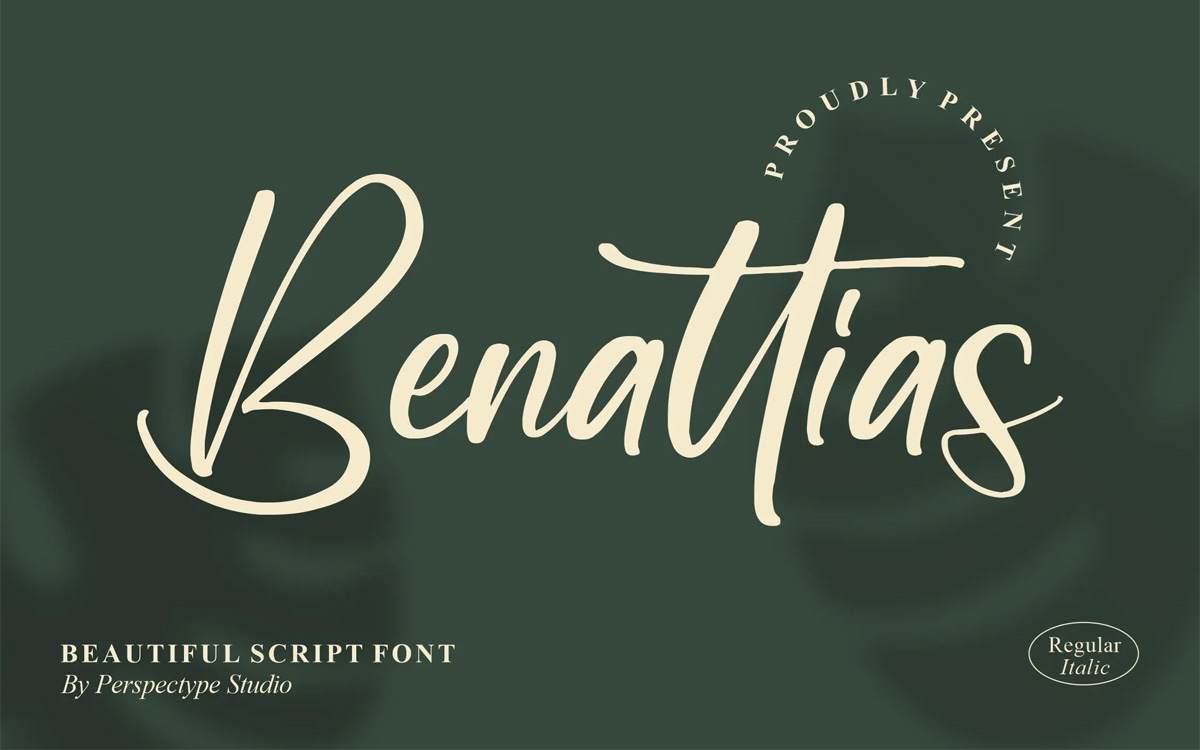
Font chữ viết tay, chữ ký mềm mại cho thiệp cưới, đám cưới TH Benattias
Trong thiết kế thiệp cưới, việc lựa chọn bộ font chữ phù hợp đóng vai trò quyết định tạo nên ấn tượng đầu tiên sang trọng và tinh tế cho ngày trọng đại. TH Benattias là bộ font chữ viết tay, chữ ký mềm mại đỉnh cao được thiết kế dành riêng cho các ấn phẩm đám cưới, mang đến phong cách nghệ thuật quyến rũ và xúc cảm chân thành. Với đường nét uốn lượn tự nhiên, TH Benattias chắc chắn sẽ nâng tầm đẳng cấp cho tấm thiệp cưới của bạn, biến từng nét chữ thành một tác phẩm nghệ thuật đong đầy hạnh phúc.
Dù bạn là một designer chuyên nghiệp đang tìm kiếm bộ chữ hoàn hảo cho bộ sưu tập mẫu thiệp mới, hay là cô dâu chú rể muốn tự tay chăm chút cho ngày vui của mình, TH Benattias đều sẵn sàng đáp ứng những tiêu chuẩn khắt khe nhất về tính thẩm mỹ. Hãy cùng khám phá chi tiết về bộ font chữ viết tay cực kỳ độc đáo này ngay dưới đây.
Vẻ Đẹp Độc Bản Từ TH Benattias – Font Chữ Viết Tay, Chữ Ký Mềm Mại Cho Thiệp Cưới Và Đám Cưới Sang Trọng
Ngày cưới là sự kiện trọng đại nhất trong cuộc đời mỗi người, nơi từng chi tiết nhỏ nhất từ không gian, hoa trang trí cho đến tấm thiệp mời đều cần chứa đựng sự tỉ mỉ và tâm huyết. Việc ứng dụng font chữ viết tay, chữ ký mềm mại cho thiệp cưới, đám cưới TH Benattias chính là bí quyết giúp bạn gửi gắm lời mời trân trọng nhất tới những người thân yêu. Không đơn thuần là các ký tự vô giác, TH Benattias thổi hồn vào không gian tiệc cưới bằng vẻ đẹp lãng mạn, phóng khoáng nhưng không kém phần quý phái.
Sở dĩ bộ font này tạo nên cơn sốt trong cộng đồng thiết kế đám cưới là nhờ sự kết hợp tài tình giữa nét bút lông mềm mại (brush script) và nghệ thuật viết chữ ký (signature calligraphy). Các đường nét của font TH Benattias có độ dày mỏng chuyển biến linh hoạt, mô phỏng chính xác nhịp điệu của bàn tay nghệ nhân khi nắn nót từng nét chữ. Sự tự nhiên này xóa tan cảm giác cứng nhắc của các font chữ máy tính thông thường, mang lại cảm giác thân thiện, ấm áp và vô cùng cao cấp.</p>
1. Thiết Kế Nét Chữ Mềm Mại, Bay Bổng Mang Tính Nghệ Thuật Cao
Tính năng nổi bật nhất của TH Benattias chính là cấu trúc nét chữ vô cùng uyển chuyển. Mỗi đường móc, nét uốn đều được tính toán tỉ mỉ để tạo nên sự cân bằng hoàn hảo giữa tính dễ đọc và vẻ đẹp nghệ thuật. Nét bút mang lại cảm giác phóng khoáng, nhẹ nhàng như những dải lụa mềm mại đang tung bay trong gió thu tiệc cưới.
Đối với các thiết kế thiệp cưới hiện đại, nét chữ viết tay này giúp tôn vinh tên của chú rể và cô dâu (Monogram/Couple Name), biến điểm nhấn chính trên tấm thiệp trở nên nổi bật và thu hút ánh nhìn ngay từ giây đầu tiên. Bên cạnh đó, font chữ còn giữ được độ thanh thoát dù ở kích thước lớn hay nhỏ, giúp trang trí các tiêu đề thiệp vô cùng ấn tượng.
2. Hệ Thống Ký Tự Thay Thế (Swashes) Phong Phú Cho Chữ Ký Độc Đáo
Một bộ font chữ ký đẳng cấp không thể thiếu các ký tự thay thế (Glyphs & Swashes) và TH Benattias đã làm xuất sắc điều này. Bộ font cung cấp hàng loạt tùy chọn nét gạch chân, nét bay ở đầu và cuối từ (Beginning & Ending Swashes), giúp người thiết kế biến tấu linh hoạt mà không sợ bị trùng lặp.
• Nét uốn đầu và cuối từ: Tạo cảm giác chữ viết tay tự nhiên như một chữ ký nghệ thuật chuyên nghiệp.
• Ligatures (Nét nối đôi): Các cặp chữ cái đặc biệt được nối liền mạch một cách tinh tế, xóa bỏ khoảng cách thô cứng giữa các ký tự.
• Bộ ký tự mở rộng: Cung cấp nhiều dạng nét uốn cho các chữ cái hoa, giúp các mẫu logo tên đám cưới trở nên độc bản.
3. Hỗ Trợ Tiếng Việt Trọn Vẹn, Chuẩn Tỷ Lệ Ký Tự
Rất nhiều bộ font script nước ngoài gặp phải rào cản lớn khi áp dụng vào tiếng Việt: các dấu thanh (sắc, huyền, hỏi, ngã, nặng) thường bị đè lên nét chữ hoặc làm mất đi vẻ thẩm mỹ vốn có. Tuy nhiên, TH Benattias đã được Việt hóa chỉn chu, đảm bảo giữ nguyên tinh thần thiết kế ban đầu.
Các dấu tiếng Việt trong TH Benattias được đặt ở vị trí tối ưu, có tỷ lệ hài hòa với tổng thể chữ cái. Điều này giúp các câu từ tiếng Việt như “Trân trọng kính mời”, “Lễ Thành Hôn”, “Lễ Vu Quy” hay tên riêng của dâu rể thể hiện mượt mà, không xảy ra hiện tượng dính nét hay lỗi font hệ thống. Đây chính là điểm cộng tuyệt đối giúp TH Benattias trở thành sự lựa chọn hàng đầu cho các nhà thiết kế thiệp cưới tại Việt Nam.
4. Ứng Dụng Đa Dạng Trong Hệ Sinh Thái Thiết Kế Đám Cưới
Không chỉ giới hạn ở chiếc thiệp mời truyền thống, TH Benattias sở hữu khả năng ứng dụng linh hoạt trên toàn bộ hệ sinh thái nhận diện đám cưới (Wedding Branding). Bạn có thể dễ dàng đồng bộ phong cách chữ này trên nhiều ấn phẩm khác nhau:</p>
1. Thiệp cưới & Phong bì thư: Làm nổi bật tên cô dâu – chú rể, trích dẫn ngôn tình hoặc các câu slogan tình yêu.
2. Bảng Đón Khách (Welcome Board): Tạo điểm nhấn sang trọng ngay tại cổng đón khách của nhà hàng hay không gian tiệc ngoài trời.
3. Menu tiệc cưới & Số bàn (Table Numbers): Giúp không gian bàn tiệc thêm phần tinh tế, cao cấp.
4. Thẻ Cảm Ơn (Thank You Cards) & Quà tặng khách mời: Gửi gắm sự chân thành qua nét chữ ấm áp, đậm chất cá nhân.